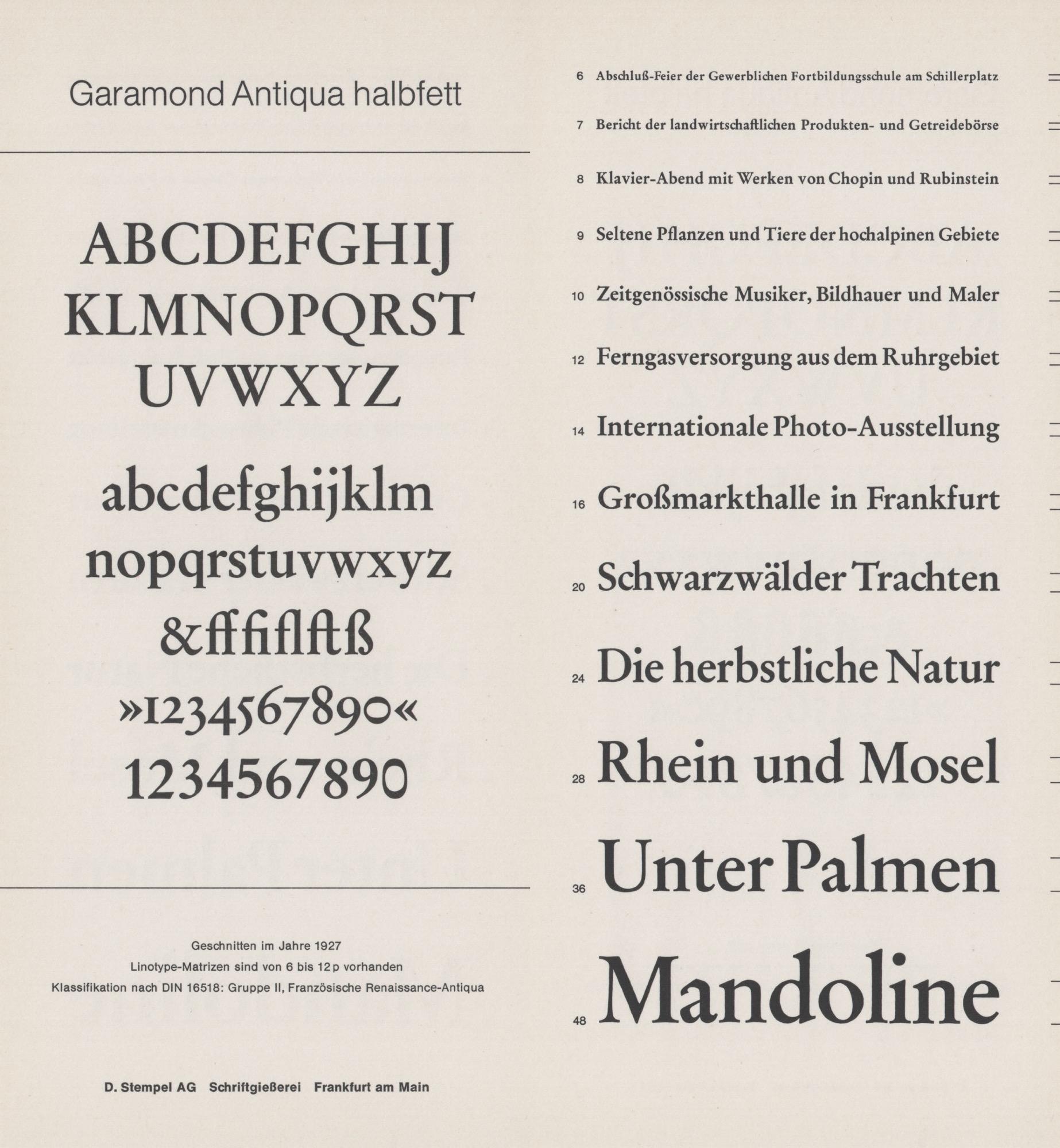
Die Stempel Garamond ist eine Interpretation der Schriften Claude Garamonds, die auf Schriftmuster der Gießerei Egenolff-Berner zurückgehen und in den 1920er- und 1930er-Jahren bei D. Stempel erschien.
Foundry: D. Stempel Linotype
erschienen: 1925
Art: serif
Formprinzip: Antiqua humanistisch